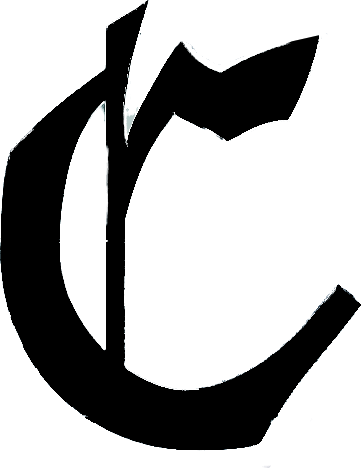
Schrift oder ähnliche Schrift gesucht.
Hey, wollte einfach mal fragen ob mir die typografie Profis hier nen kleinen Tipp geben könnten:
Wäre Wahnsinn wenn mir jemand den genauen Namen des Fonts sagen könnte :D
Sonst wäre ein sehr ähnlicher auch sehr schön^^
Eventuell auch an dem hier orientieren.
EDIT: Sorry, wollte noch aussagekräftiger in den Titel "Gothic" schreiben, aber darf man ja im nachhinein nicht mehr ändern....
In deinem Beispiel ist sie horizontal gestaucht. Das tut man aber eigentlich nicht.
Ich dachte mir auch Lucida aber ich kam nicht mehr drauf welcher genau...